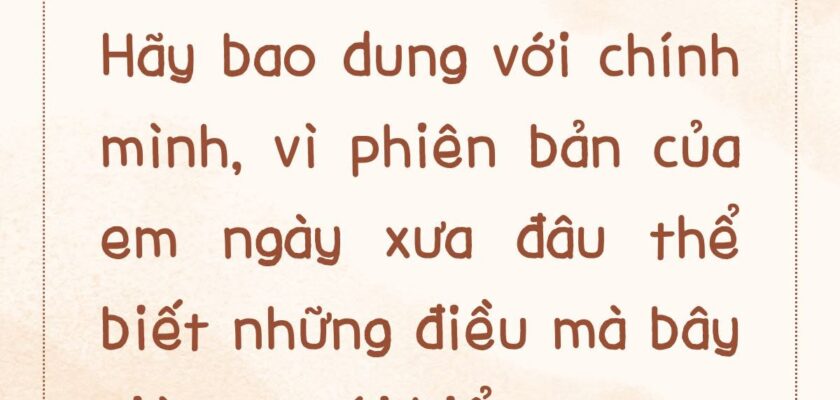
Việt hóa theo yêu cầu 25 || LF Sweet Peachy
- Tác giả: soffr_nv
- Việt hóa: lengnef
Sweet Peachy là kiểu font viết tay dễ thương được tác giả share trên Threads, hợp với nhiều thiết kế dưỡng thê, hoặc đổi font trong điện thoại. Font này cũng đã được gắn dấu phần pinyin.